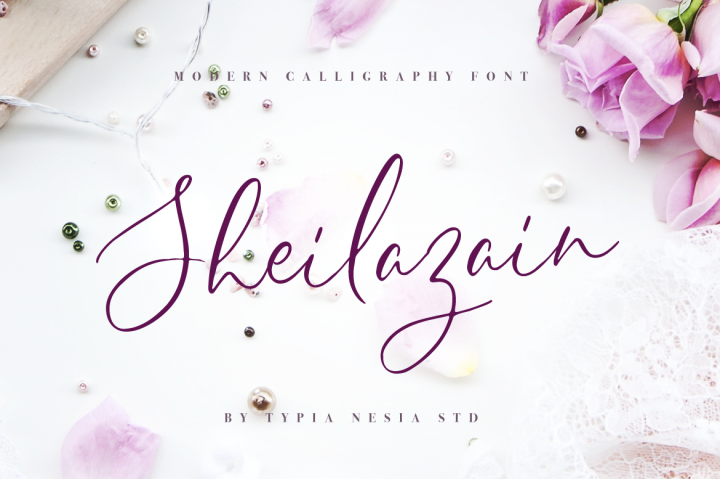
Sheilazain Script Font – Download Grátis
Olá! Estou aqui para apresentar a fonte Sheilazain Script Font – uma nova font elegante com um ar romântico e natural. Especialmente criada por Hamilton, esta font cai bem como um charuto nas criações de design moderno que você está planejando fazer. Ideal para seus projetos futuros, a Sheilazain Script é perfeita para design de convites moderno, identidade de marca, papelaria, blog, design publicitário moderno, cartões de convite, citações artísticas, decoração de casa e até mesmo capas de livros ou títulos. E se você estiver procurando por uma fonte de escrita cíntica elegante para eventos especiais como casamentos, aniversários e muito mais, a Sheilazain Script é a escolha certa. A Sheilazain Script foi projetada com um toque moderno e elegante, dando ao seu design aquela pitada única de sofisticação que você tanto procura. É uma fonte perfeita para quando deseja criar algo notável e especial em qualquer projeto que esteja fazendo.